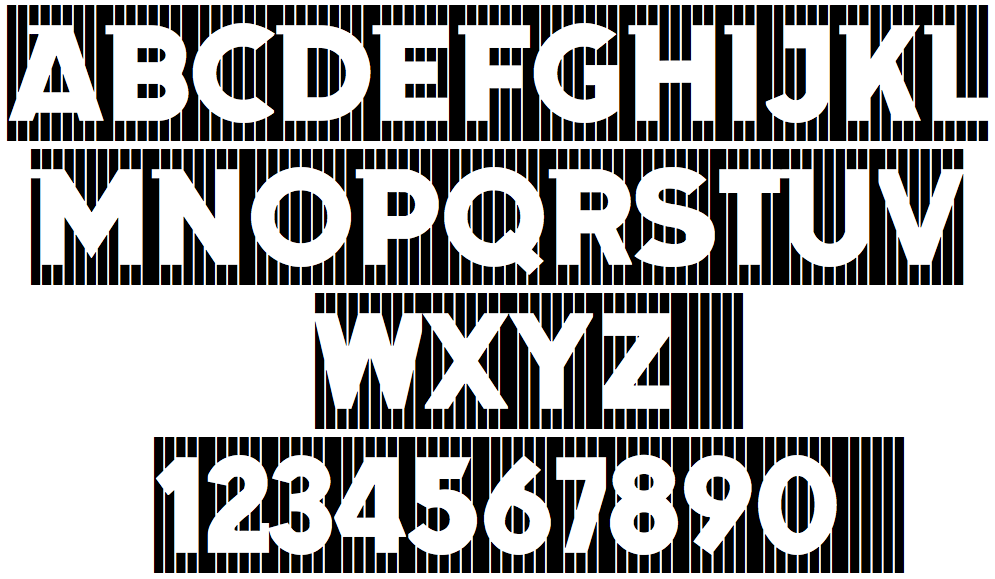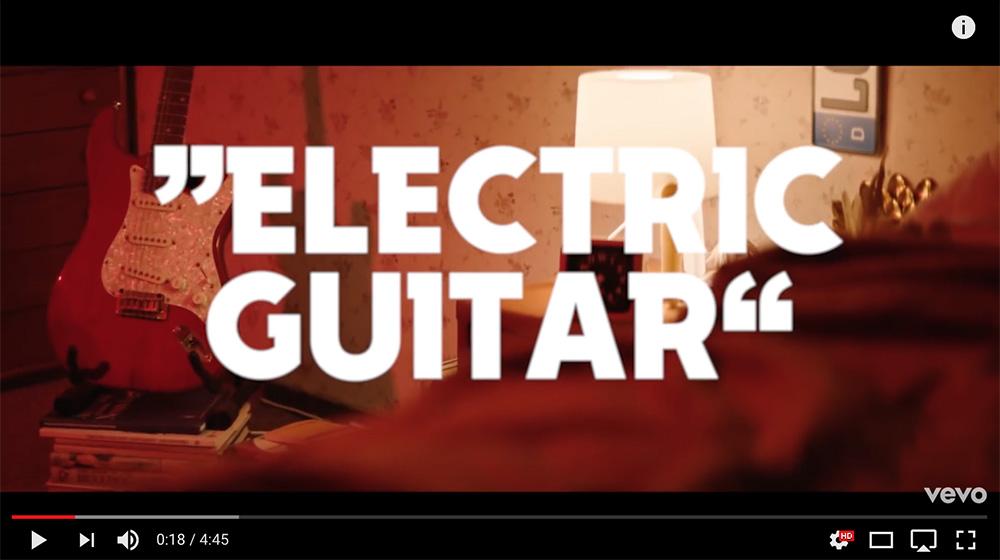
Suche Schrift von »Electric Guitar« aus Tocotronic-Video
Aber diese Schriftart, die in diesem (und anderen) Tocotronic-Video verwendet wird – und so eine Art Hauschrift zu sein scheint (siehe Plakat) – unterscheidet sich dann doch schon ganz ordentlich von der Motorcross und der Dynamo. Besonders bei den "komplizierteren" Formen. Bin gespannt, ob jemand den Namen der Schrift und vielleicht sogar die Hintergründe der Entstehung herausbekommt.
darum schrieb ich ja "ähnlich".
das logo gibts ja schon seit den anfängen der tocos und ich vermutete das ein grafikdesigner irgendwann mal die schrift auf basis diesem logo erstellt hat. man müsste mal recherchieren seit wann die schrift eingesetzt wird und wer das plattendesign damals gemacht hat. evtl. wissen die kollegen mehr über die entstehung:
Denkbar auch dass Arne sich da als Illustrations-Student damals einfach selbst betätigt hat, erst DIY beim Logo (das schon auf der Digital Ist Besser so drauf ist) und dann eben mal auch bei der Schrift.
Mögliche Inspirationsquelle, gerade im Regal entdeckt – Cover von Heinz Edelmann (obwohl ja Michael Ende näher liegen würde)
Das ist ja die oben bereits genannte »Dynamo«.
Ein Element, das von Anfang an bei fast jeder Tocotronic-Platte auftaucht, ist euer Logo…
Das hat unser Schlagzeuger Arne, der mal Illustration studiert hat, gemacht. Im Keller der Schule hatten die eine alte Bleisatz-Werkstatt und dort hat er das Logo gedruckt.
Ich muss mal schauen, aber ich müsste eigentlich noch irgendwo einen Tocotronic-Aufkleber aus der »Digital ist besser«-Zeit rumfliegen haben. Allerdings Siebdruck auf Neonklebefolie ...
Das dunkelblaue mit der Kritzeltypo drauf? Das müsste ich auch noch irgendwo haben – nebst dem »Tocotronic hat mein Leben zerstört«-Shirt.
Hallo, falls es noch jemanden interessiert: Die Schrift ist tatsächlich von  Tim Wetter (damals bei jung und wenig) und mir (damals HGB Leipzig, Typedesign-Klasse von Stephan Müller und Fred Smeijers) für Tocotronic neu gezeichnet worden.
Das Logo wurde ursprünglich, wie von einem User hier richtig erkannt, in den Schäfer-Versalien gesetzt. Wir haben uns nicht nur aus urheberrechtlichen Bedenken entschieden, diese nicht zu "digitalisieren"; die Schäfer-Versalien sind, als Akzidenzschrift, auch einigermaßen eigenwillig im Satz und wir wollten keinen Retro-Kitsch produzieren. Die Ähnlichkeit mit der Motor kommt daher, dass wir diese Haken links auf Balkenstärke gebracht haben. Wir haben aber auch einen Schnitt ohne die überstehenden Balken gemacht. Nach unserer Interpretation kamen die Haken der Schäfer-Versalien daher, dass Karl Hermann Schaefer sich an mit Pinsel geschriebenen Buchstaben orientiert hat. Dies war für uns, wie das Genre der reinen Akzidenzschrift, ästhetisch nicht mehr vertretbar, da heute, anders als in 1920er-Jahren, praktisch keine mit Pinsel geschriebene Schrift im öffentlichen Raum mehr zu sehen ist.
Die Entscheidung für eine konstruiertere und zeitgenössische Form hat zum Ergebnis, dass das Band-Logo nicht exakt in der Schrift nachgebaut werden kann, was in der Band teilweise zunächst nicht ganz verstanden wurde. Die bessere Präsenz im Satz hatte sich aber wie gesagt schon im Gestaltungsprozess gegen das bloße Kopieren der Einzelformen der Schäfer-Versalien bes. des Ps Rs und Bs durchgesetzt.